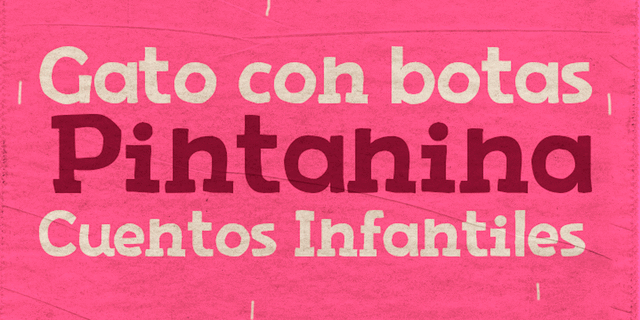
Марти – неформальный рисованный брусковый шрифт с игривым мальчишеским настроением. Он поддерживает множество европейских языков, а также кириллицу. Этот шрифт имеет богатые возможности в виде альтернативных глифов, росчерков и редких лигатур. Шрифт Марти разработал Родриго Арая Салас в 2014 году.
Ассоциации c начертанием Marty RegularКачества и характер:
уличный, городской, крафтовый, неформальный, мультяшный, ручной, рукотворный, кустарный, самодельный, живой, ламповый, заметный, выразительный, неряшливый, ремесленный, забавный, ироничный, крепкий, здоровый, бодрый, сильный, деревенский, старомодный, ковбойский, мачо, фермерский, веселый, смешной, дружелюбный, добродушный, добрый, игривый, подвижный, свежий, спелый, вкусный, тяжелый, детский, наивный, карикатурный, милый, остроумный, летний, счастливый, грубый, оригинальный, характерный, неотесанный, неровный, праздный, гуляющий, балованный, угловатый, круглый, щедрый, интересный, деревянный, прямоугольный, квадратный, студенческий, тусовочный, прикольный, творческий, симпатичный, артизанальный, небрежный, вернакулярный, игровой
дача, хенд мейд, отдых, природа, анимация, мультфильм, закуска, фаст фуд, торговля, лавка, школа, дневник, город, граффити, магазин, игра, одежда, обувь, еда, мясо, ферма, джинсы, ранчо, трактир, ковбой, обед, ужин, гамбургер, канцтовары, завтрак, юмор, лагерь, кружок, карандаши, игрушка, детская книжка, раскраска, специи, тетрадь, конструктор, приключения, кубики, развлечения, вечеринка, каникулы, наклейка, стикер, лего Стилистика: